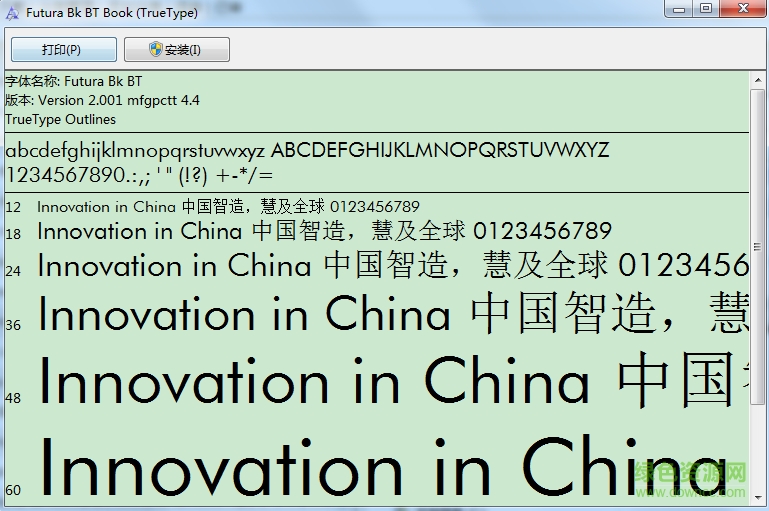
futura bk bt是一款非常漂亮的英文字體,這款字體精簡大氣,深沉穩(wěn)重,給人一種嚴(yán)謹(jǐn)莊嚴(yán)之感,受到眾多用戶的喜愛,歡迎需要的朋友來綠色資源網(wǎng)下載體驗(yàn)!
futura bk bt字形清秀大方,華而不浮,非常適合廣告設(shè)計(jì)、平面設(shè)計(jì)、印刷包裝、正文標(biāo)題等人員使用。